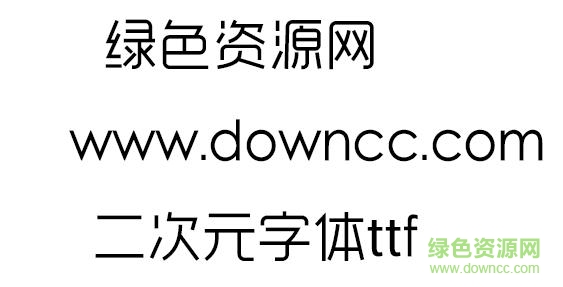
二次元字体ttf是一款最美的混搭二次元字体,让你在使用的时候能够感受到浓厚的二次元气息,从而在二次元中进行文字输入以及艺术字制作,让二次元的小伙伴们都感受到最佳的字体视觉体验,快来绿色资源网下载吧!
这款字体在二次元中十分流行,我就是通过二次元小伙伴推荐的,十分的好看,它的字体样式十分规整,同时也透着俏皮的特色,我很喜欢!